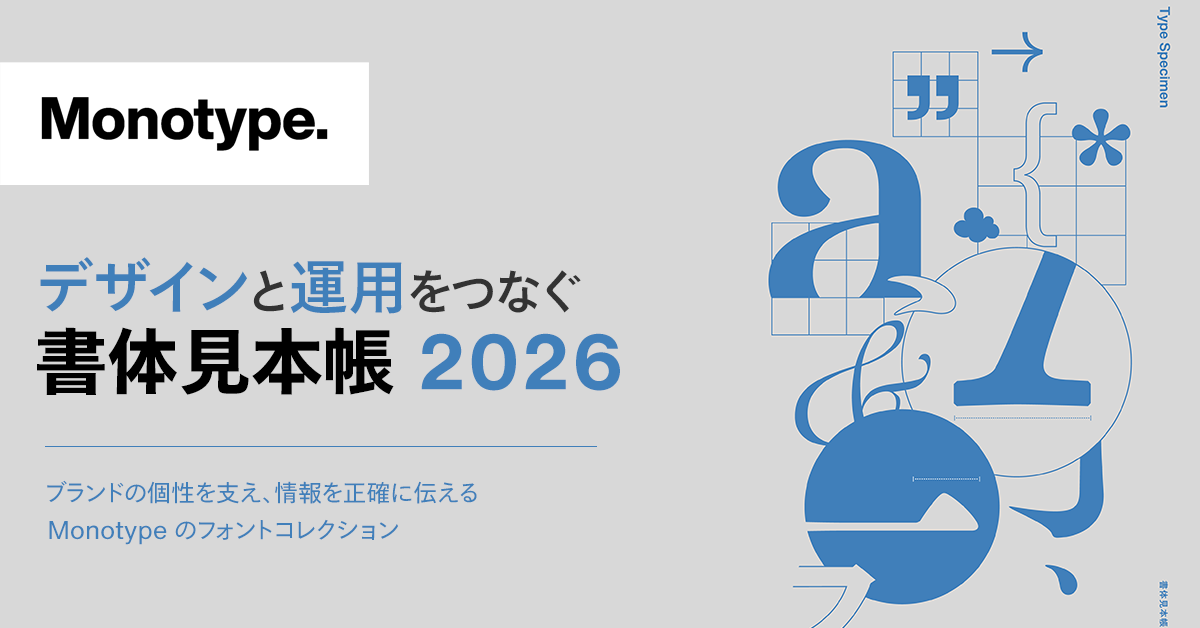
デザインと運用をつなぐ、Monotypeのフォントコレクション
書体見本帳 2026
ブランドの個性を伝え、体験を形づくるフォント。
「書体見本帳 2026」では、Monotypeの和文・欧文・和欧混植フォントを、実際の使用イメージとともにご紹介します。
ブランドデザイン、広告・販促物、Webサイト、アプリケーションなど、さまざまなコミュニケーションシーンにおいて、書体がどのような印象を生み出すのかを一冊にまとめました。
フォント選定の参考資料として、ぜひご活用ください。
フォント選びのインスピレーションに
書体は、単なる文字ではなく、ブランドの声や個性を伝える重要な要素です。
本見本帳では、書体ごとの特徴や表現の違いを比較しながら、ブランドデザインや日々の制作業務に役立つヒントをご覧いただけます。
掲載内容
・使用イメージ
・和文フォント
・欧文フォント
・和欧混植フォント
書体が変わると、伝わり方も変わる
同じ言葉でも、書体によって受ける印象は大きく変化します。
信頼感、先進性、親しみやすさ、上質感。
ブランドが伝えたい価値をどのように表現するか。そのヒントを、本見本帳でご覧ください。